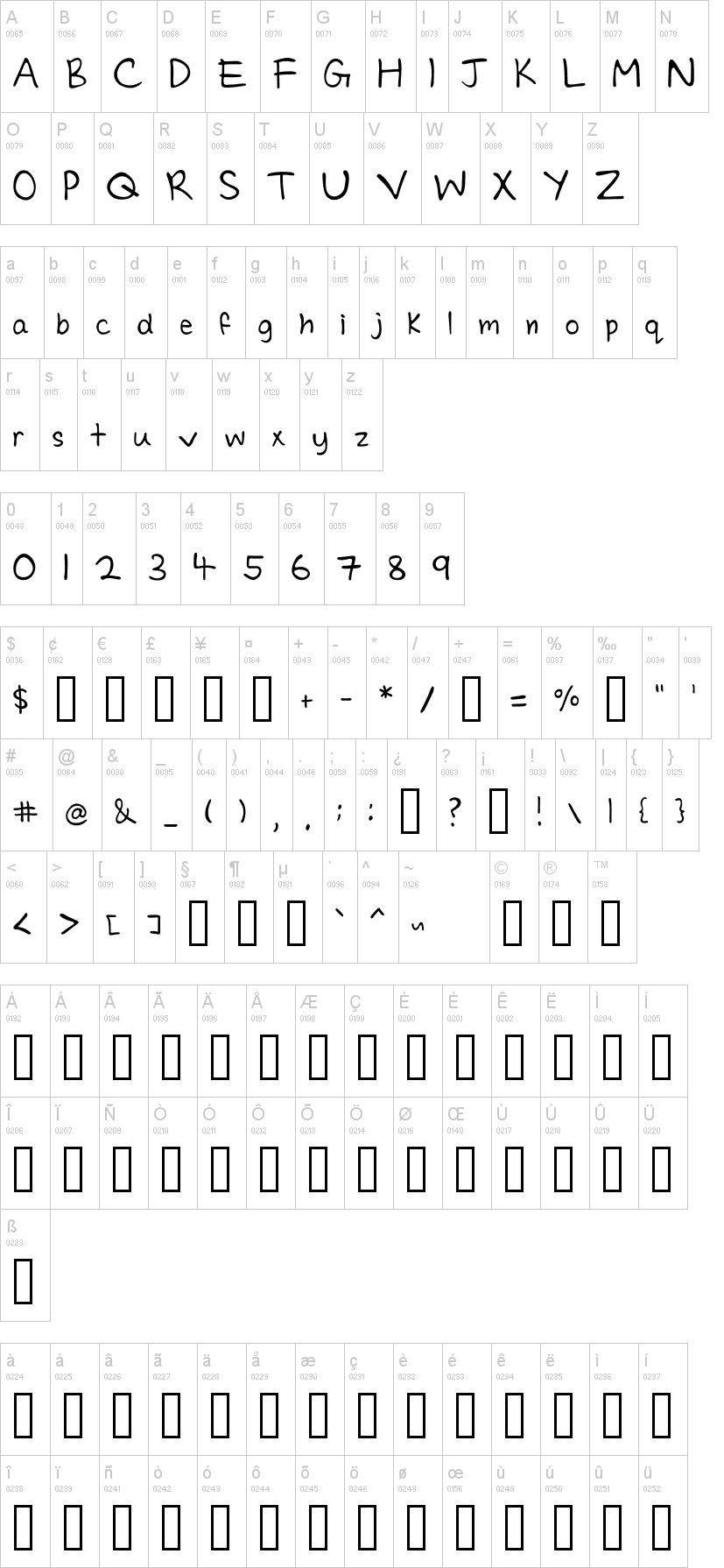
Charmie 字体是一种简洁、清新、可爱的英文字体,它有着华丽而流畅的设计,完美地表达出温暖可爱的感觉。它具有更大的可读性,可以帮助您在设计中呈现出更多的情感。它也可以帮助您创造出更多的视觉效果,从而使您的设计更加出色。内容介绍
Charmie是一款非常不错的手写艺术字体,具有很好的视觉感,适合于文化类的宣传设计、商业类品牌的广告和产品包装设计以及个性化文字排版等较多场景。